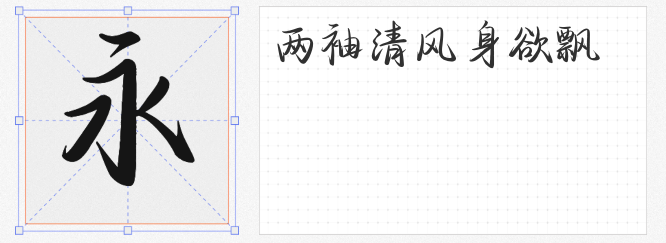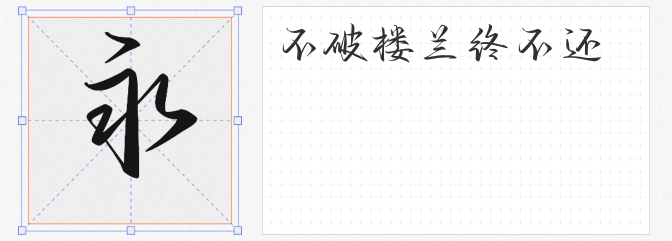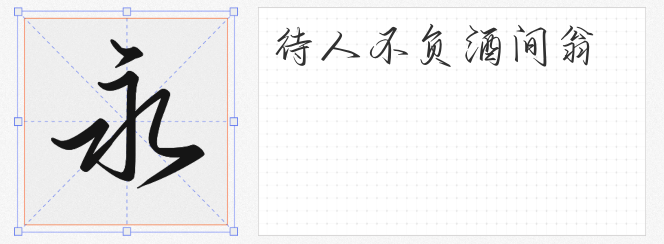
在手写字体中,每一款都有其独特的韵味和风格。今天,为大家推荐四款极具特色的手写字体。这些字体不仅美观大方,而且各具特色,能够满足不同设计需求。
首先,让我们来看看“字圈也字望春风楷书”。这款字体带有浓厚的书卷气息,笔画流畅而自然,既有楷书的工整,又融入了草书的洒脱。其连笔勾丝、横笔左低右高的设计,使得整个字体看起来既和谐又富有变化。从视觉效果上来看,这款字体起笔落笔连贯,颇有艺术美感,仿佛一幅流动的山水画,诗情画意,别有一番风情。
接下来是“字圈也字侠客行”。这款行楷书法字体视觉效果极为舒服,笔画起止转折上既有圆的柔美,又有方的刚劲。行楷的斜撇略带弯度,显得字体俏皮而不呆板;中竖居正,中横斜式、横档等距,使得整个字体看起来既平稳又和谐。线条粗细变化明显,连笔牵丝,笔断而气息不断,笔意连绵不绝,自成风格,仿佛一位侠客在江湖中自由驰骋。
再来看看“字圈也字醉寒江行草”。这款字体下笔收笔、起承转合皆保留了字体个性,同时优化了字体笔迹,使得其易识性更强。整个字体看起来仿佛一位将赴盛宴的翩翩才子,胸有成竹,张弛有度。其笔画既有行草的奔放,又不失字体的端庄和稳重。
最后是“字圈也字风满袖行楷”。这款字体在保留了楷书结构特点的同时,加入了一些行书的笔意。既保证了其点画位置的严谨性,又借鉴了书法里“游丝引带”的方法制作了连笔,给人以行云流水之观感。左勾竖出峰有力,增添了几分荡气回肠的魄力。整个字体看起来既潇洒又大气,非常适合用于需要展现力量和魄力的设计作品。
以上就是我为大家推荐的四款手写字体。每一款都有其独特的韵味和风格,能够满足不同设计需求。希望这些字体能够为您的设计作品增添一份独特的魅力。